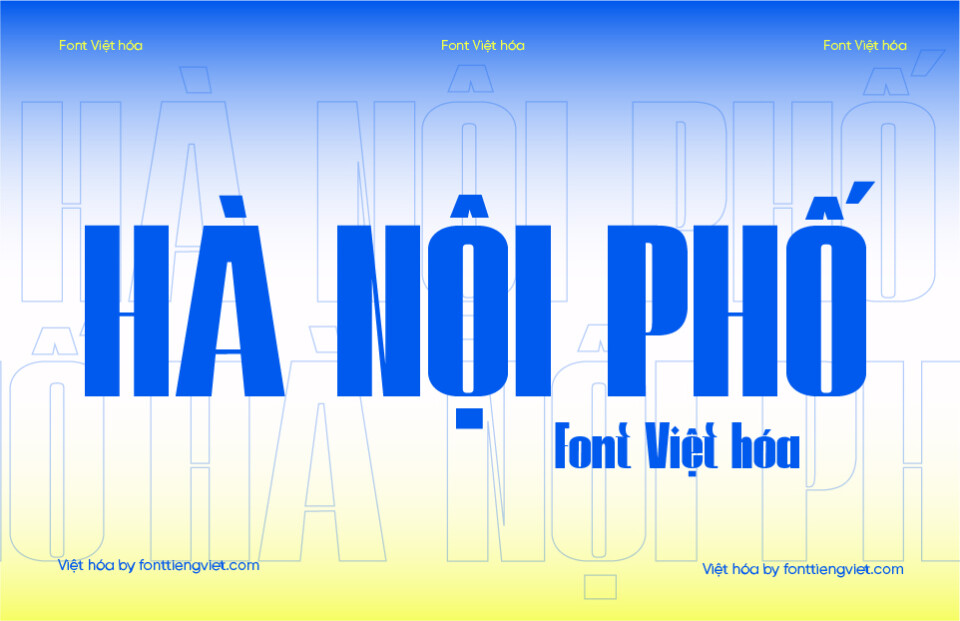
Font Việt hóa 1FTV VIP Mordie
Giới thiệu về Font Việt hóa 1FTV VIP Mordie
Trong thế giới thiết kế đồ họa hiện đại, việc tìm kiếm một bộ Font Miễn Phí chất lượng luôn là ưu tiên hàng đầu của các bạn học sinh và giáo viên. Font Việt hóa 1FTV VIP Mordie nổi lên như một lựa chọn hoàn hảo nhờ sự kết hợp tinh tế giữa nét chữ cổ điển và phong cách hiện đại. Đây là bộ font được tinh chỉnh kỹ lưỡng về dấu tiếng Việt, giúp người dùng không còn lo lắng về lỗi hiển thị khi soạn thảo văn bản hay làm slide bài giảng.
Đặc điểm nổi bật của bộ font chữ này
Bộ Font Việt hóa 1FTV VIP Mordie sở hữu những đường nét thanh mảnh nhưng vô cùng chắc chắn, mang lại cảm giác chuyên nghiệp cho mọi dự án. Điểm cộng lớn nhất chính là khả năng ứng dụng đa dạng từ thiết kế bìa sách, áp phích sự kiện trường học cho đến các thiệp mời trang trọng. Với bộ ký tự đầy đủ, bạn có thể tự do sáng tạo mà không gặp bất kỳ rào cản kỹ thuật nào.
Cách ứng dụng Font Việt hóa 1FTV VIP Mordie hiệu quả
Sử dụng trong học tập và giảng dạy
Học sinh có thể dùng bộ font này để làm nổi bật các tiêu đề trong bài thuyết trình PowerPoint, giúp bài làm trở nên thu hút và dễ theo dõi hơn. Đối với giáo viên, Font Việt hóa 1FTV VIP Mordie là công cụ đắc lực để thiết kế các bảng tin lớp học hoặc tài liệu ôn tập sinh động, khơi gợi hứng thú học tập cho các em học sinh một cách tự nhiên nhất.